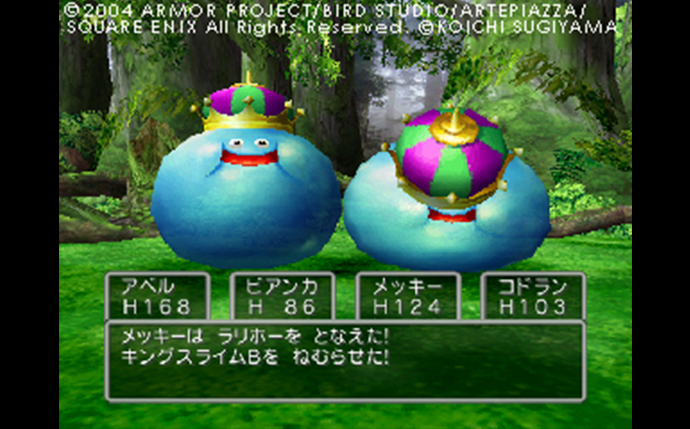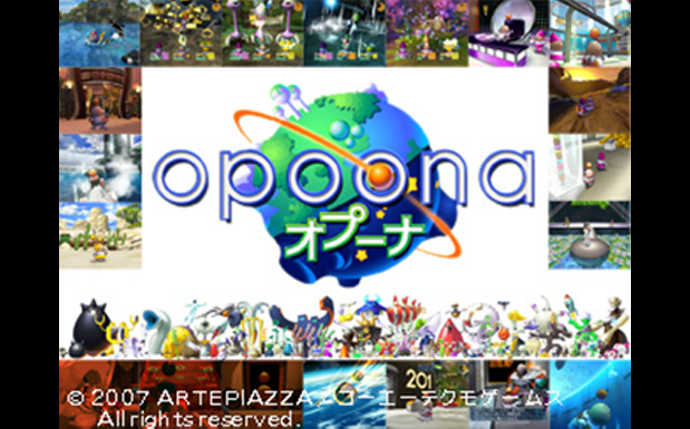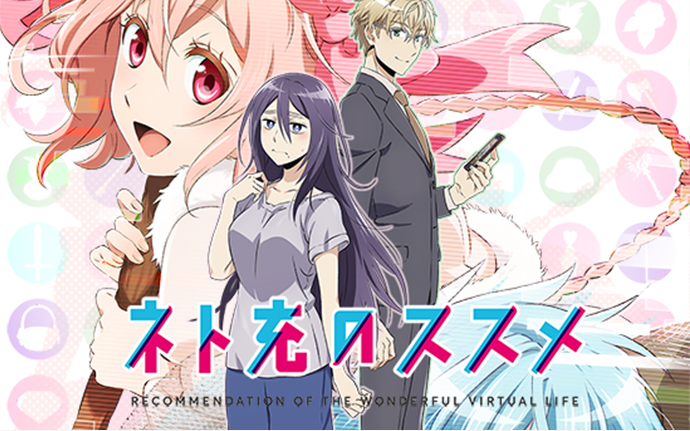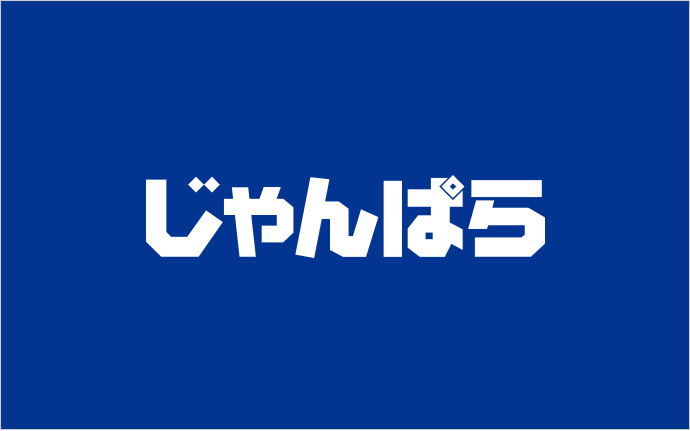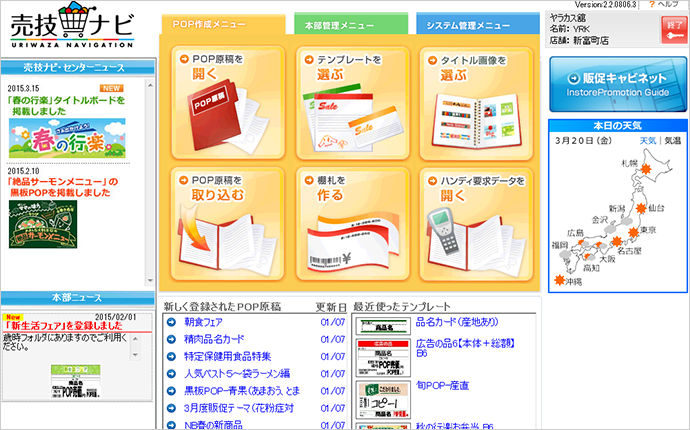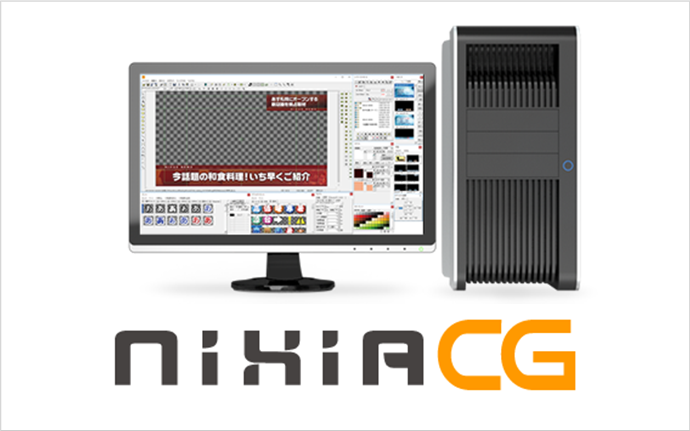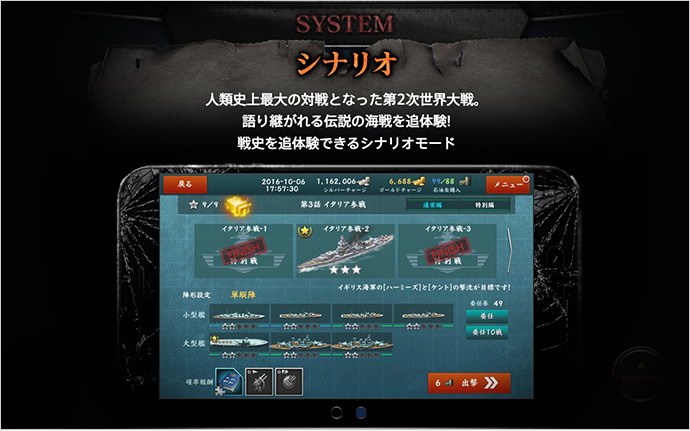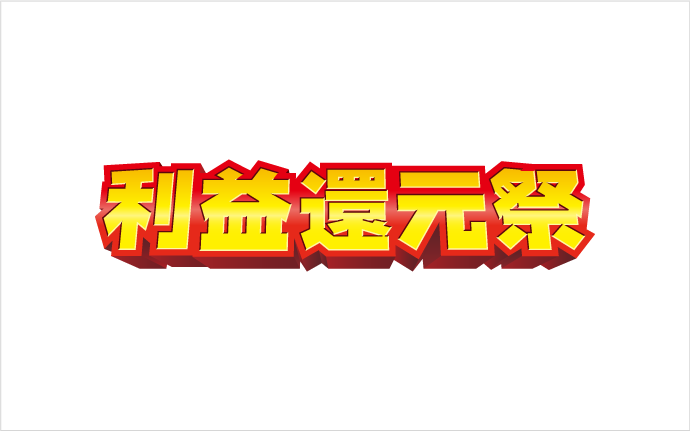
導入事例
「売上アップにつなげたい」「今すぐファンを増やしたい」など、お客様が抱える課題はさまざま。
ここでは、そんな課題解決にNIS Fontを導入いただいたお客様の事例をご紹介します。
ドラゴンククエスト(PlayStation2)
(発売元:スクウェア・エニックス)
使用フォント JTCウインR4
アルテ
ピアッツァ様
『ドラゴンクエスト』という王道で且つ親しみやすい作品には、ほどよく風格があって丸みのある、こちらのフォントがマッチするのではないか、と考えて採用させていただきました。
オプーナ(Wii)
(発売元:コーエーテクモゲームス)
使用フォント JTCウインS4
アルテ
ピアッツァ様
『オプーナ』は独特な世界観でありながらもゲームとして王道のRPGでしたので、風格がありつつも遊びのあるフォントがマッチするのではないか、と考えて採用させていただきました。
バトルシップウォーズ(ゲーム)
使用フォント JTC直線江戸文字「剣」 他
コンゾン様
弊社ゲームタイトルの世界観や雰囲気に相応しく、貴社フォントを採用させて頂いた決め手となりました。
じゃんぱら(店舗ロゴ)
使用フォント JTCウインZ10
サードウェーブエクスチェンジ様
じゃんぱらは秋葉原のパソコンパーツの買取で培った高い技術力を生かしスマートフォン、PC、AV機器買取・販売および修理(一部端末)を行っています。【技術に裏打ちされた信頼】をイメージさせるしっかりした力強いこのフォントを選択しています。
ネト充のススメ(アニメ)
使用フォント S明朝ソフトW5
シグナル・
エムディ様
いわゆるアニメアニメしたポップな書体で雰囲気を作るのではなく、あくまでサブタイトルのメッセージがきちんと視聴者に届くように、誠実な佇まいでありながら、かつ堅苦しくなく、親しみやすさも兼ね備えたフォントを選ぶうち、角のない優しい明朝体、S明朝に辿り着きました。
nixia CG
(ケーブルテレビ局向けテロップシステム)
使用フォント JTCウインM8
NIXUS様
テレビ局向けテロップシステム「nixiaCG100」に採用いただいております。バラエティやニュースなど、さまざまなニーズに応えられるよう、5書体を標準パッケージとしてご提供。美しく読みやすい、洗練されたフォントが、高クオリティのテロップ作成を実現します。
売技ナビ
(クラウド型POPシステム)
使用フォント 基本書体セット
ヤラカス舘様
利益還元祭(動画広告)
使用フォント JTCウインZ10
ジャパネット
ホールディングス様
使用フォント
JTCじゃんけんU
グリー様
使用フォント
JTCウインR1 他
サイバーエージェント様
使用フォント
JTCウインS6 他
フジテレビジョン様